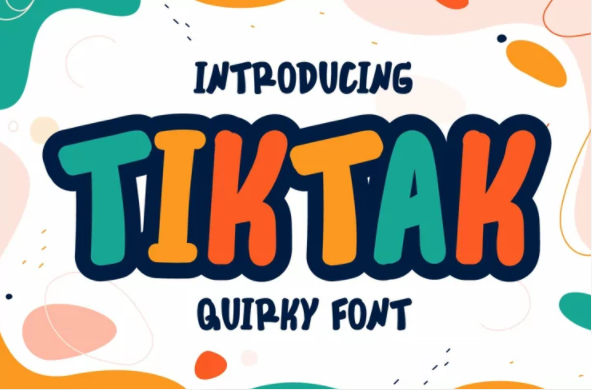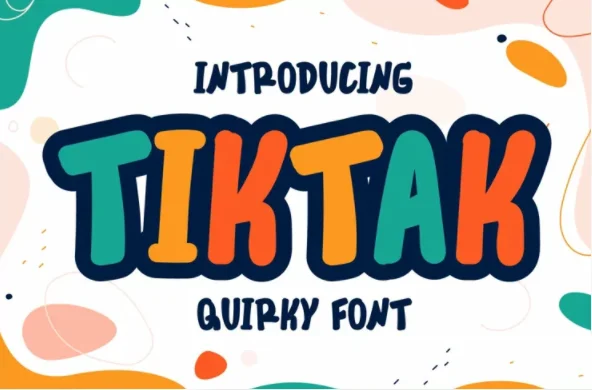
Tik Tak
- это смелый маркерный тематический шрифт.
Tik Tak идеально подходит для плакатов, футболок, обложек книг, упаковок, наклеек, цитат и всех милых, толстых и очаровательных тематических дизайнов.